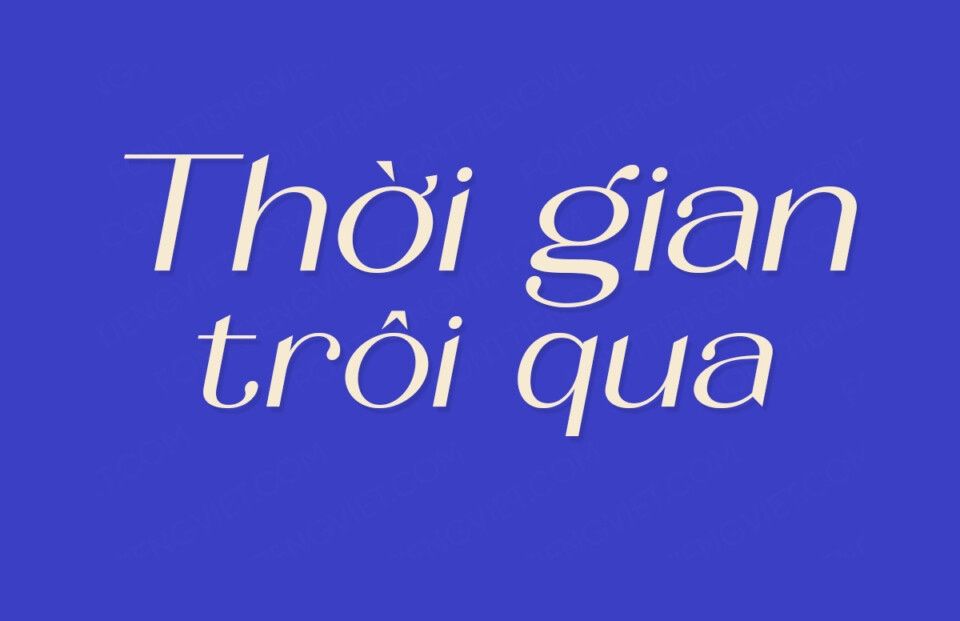
Font Việt hóa 1FTV VIP Moncer Italic
Font Việt hóa 1FTV VIP Moncer Italic là sự lựa chọn hoàn hảo dành cho các nhà thiết kế đang tìm kiếm một bộ phông chữ nghiêng vừa mang nét thanh lịch, hiện đại vừa sở hữu tính ứng dụng cao trong nhiều lĩnh vực sáng tạo. Được chế tác và tinh chỉnh chỉn chu đến từng chi tiết, bộ font này không chỉ giải quyết triệt để bài toán hiển thị tiếng Việt có dấu mà còn nâng tầm giá trị thị giác cho mọi dự án đồ họa. Dù bạn đang thực hiện bộ nhận diện thương hiệu, thiết kế thiệp cưới sang trọng hay tạo dựng hình ảnh truyền thông trên mạng xã hội, 1FTV VIP Moncer Italic sẽ luôn là điểm nhấn nghệ thuật đầy ấn tượng và khác biệt.
Khám Phá Font Việt hóa 1FTV VIP Moncer Italic – Đột Phá Thiết Kế Với Bộ Font Chữ Nghiêng Sang Trọng Và Đẳng Cấp
Trong thế giới thiết kế đồ họa đương đại, typography đóng vai trò cốt lõi trong việc truyền tải cảm xúc và thông điệp thương hiệu. Một phông chữ đẹp không chỉ giúp văn bản dễ đọc mà còn tạo nên bản sắc riêng biệt, giúp thương hiệu dễ dàng nổi bật giữa hàng ngàn đối thủ cạnh tranh. Nhận thấy nhu cầu ngày càng cao về các bộ font chữ nghiêng cao cấp hỗ trợ tiếng Việt trọn vẹn, phiên bản Font Việt hóa 1FTV VIP Moncer Italic đã được hoàn thiện như một giải pháp toàn diện cho cộng đồng designer Việt Nam.
Xuất phát từ bản gốc Moncer Italic nổi tiếng với các đường nét nghiêng phóng khoáng và cấu trúc chữ tinh tế, phiên bản Việt hóa VIP 1FTV mang đến trải nghiệm gõ tiếng Việt mượt mà và chuẩn xác tuyệt đối. Mọi dấu thanh như huyền, sắc, hỏi, ngã, nặng cùng các dấu mũ được thiết kế lại nhằm đạt tỷ lệ cân đối hoàn hảo. Điều này giúp font chữ giữ nguyên được linh hồn thiết kế ban đầu mà không bị rườm rà hay phá vỡ bố cục tổng thể khi xuất hiện các ký tự đặc trưng của tiếng Việt.
1. Đầy Đủ Bộ Ký Tự Tiếng Việt Với Tiêu Chuẩn Việt Hóa VIP Chuẩn Xác
Điểm khác biệt lớn nhất giữa phiên bản Font Việt hóa 1FTV VIP Moncer Italic và các font chữ chỉnh sửa thông thường trên thị trường chính là quy trình Việt hóa chuẩn mực và chuyên nghiệp. Toàn bộ các ký tự tiếng Việt đều được vẽ tay tỉ mỉ và đồng bộ hóa tuyệt đối với phong cách nguyên bản của tác giả gốc.
• Không lỗi font, không vỡ nét: Các ký tự có dấu được căn chỉnh khoảng cách (kerning) tự động và thủ công tỉ mỉ, đảm bảo văn bản hiển thị đẹp mắt ở mọi kích thước từ văn bản nhỏ (body text) đến các tiêu đề cỡ lớn (headline).
• Giữ nguyên tỷ lệ vàng của chữ: Dấu mũ và dấu thanh được đặt ở vị trí tối ưu, không làm dính chữ hay tạo ra các khoảng trống vô lý làm mất thẩm mỹ của trang thiết kế.
2. Nét Chữ Nghiêng Moncer Italic Thần Thái, Uyển Chuyển Và Đầy Tính Nghệ Thuật
Moncer Italic vốn nổi tiếng trong cộng đồng thiết kế quốc tế nhờ sự kết hợp hài hòa giữa đường nét hiện đại và chất nghệ thuật bay bổng. Phiên bản 1FTV VIP kế thừa trọn vẹn tinh hoa này để mang lại vẻ đẹp sang trọng, vượt thời gian cho mọi tác phẩm đồ họa.
Góc nghiêng của font được tính toán chính xác nhằm tạo cảm giác chuyển động nhẹ nhàng, thanh thoát nhưng vẫn giữ được sự vững chãi cho bố cục tổng thể. Sự tương phản tinh tế giữa nét thanh và nét đậm tạo nên chiều sâu thị giác độc đáo, giúp mỗi từ ngữ trở nên có hồn và thu hút ánh nhìn ngay từ giây đầu tiên. Phông chữ này vô cùng thích hợp cho các dự án thời trang cao cấp, mỹ phẩm, trang sức, ấn phẩm tiệc cưới, logo thương hiệu xa xỉ hay bìa tạp chí nghệ thuật.
3. Tích Hợp Hệ Thống Glyph Thay Thế (Alternates) Và Swashes Phong Phú
Để tối ưu hóa khả năng sáng tạo cho các nhà thiết kế, Font Việt hóa 1FTV VIP Moncer Italic tích hợp một thư viện phong phú gồm các ký tự thay thế (Stylistic Alternates) và nét uốn nghệ thuật (Swashes, Ligatures).</p>
• Biến hóa đa phong cách: Người dùng có thể dễ dàng thay đổi nét chữ đầu hoặc nét chữ cuối của một từ để biến một dòng văn bản đơn điệu thành một tác phẩm typographic mang đậm dấu ấn cá nhân.
• Dễ dàng truy cập qua bảng Glyph: Tương thích hoàn hảo với các tính năng OpenType trong Adobe Photoshop, Illustrator, InDesign, Figma, giúp việc tùy biến trở nên nhanh chóng và vô cùng linh hoạt.
• Tạo điểm nhấn tự nhiên: Các ký tự liên kết (Ligatures) được thiết kế khéo léo giúp các chữ cái nối tiếp nhau một cách tự nhiên như nét chữ viết tay tinh tế của một nghệ nhân calligraphy chuyên nghiệp.
4. Tính Tương Thích Cao Và Tối Ưu Cho Nhiều Phần Mềm Thiết Kế Đa Nền Tảng
Một trong những nỗi bận tâm lớn của người làm thiết kế là việc font chữ bị lỗi hiển thị khi xuất file hoặc chuyển đổi qua lại giữa các phần mềm làm việc khác nhau. Font Việt hóa 1FTV VIP Moncer Italic giải quyết triệt để nỗi lo này nhờ cấu trúc định dạng chuẩn hóa tiên tiến.